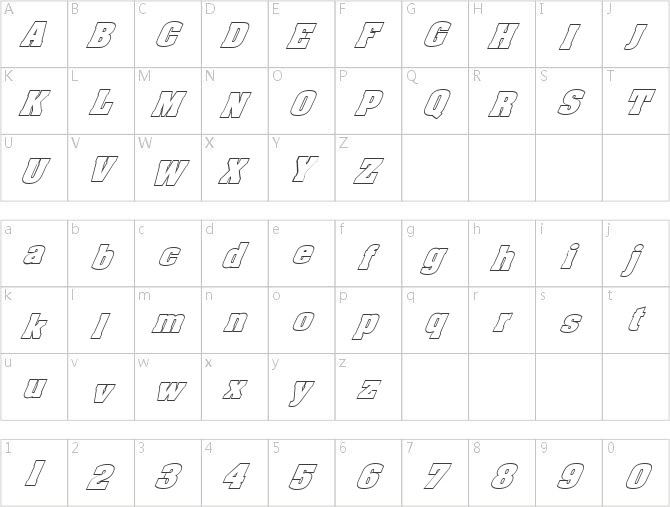
FZ BASIC 52 HOLLOW ITALIC
FZ BASIC 52 HOLLOW ITALIC介紹
FZ BASIC 52 HOLLOW ITALIC字體字庫是一款讓人賞心悅目、百看不厭的英文字體,適合各類廣告和產品包裝設計應用,字體大小0.07MB,格式為ttf字體,上傳用戶是/zyj【GF】,作者/版權方為未知